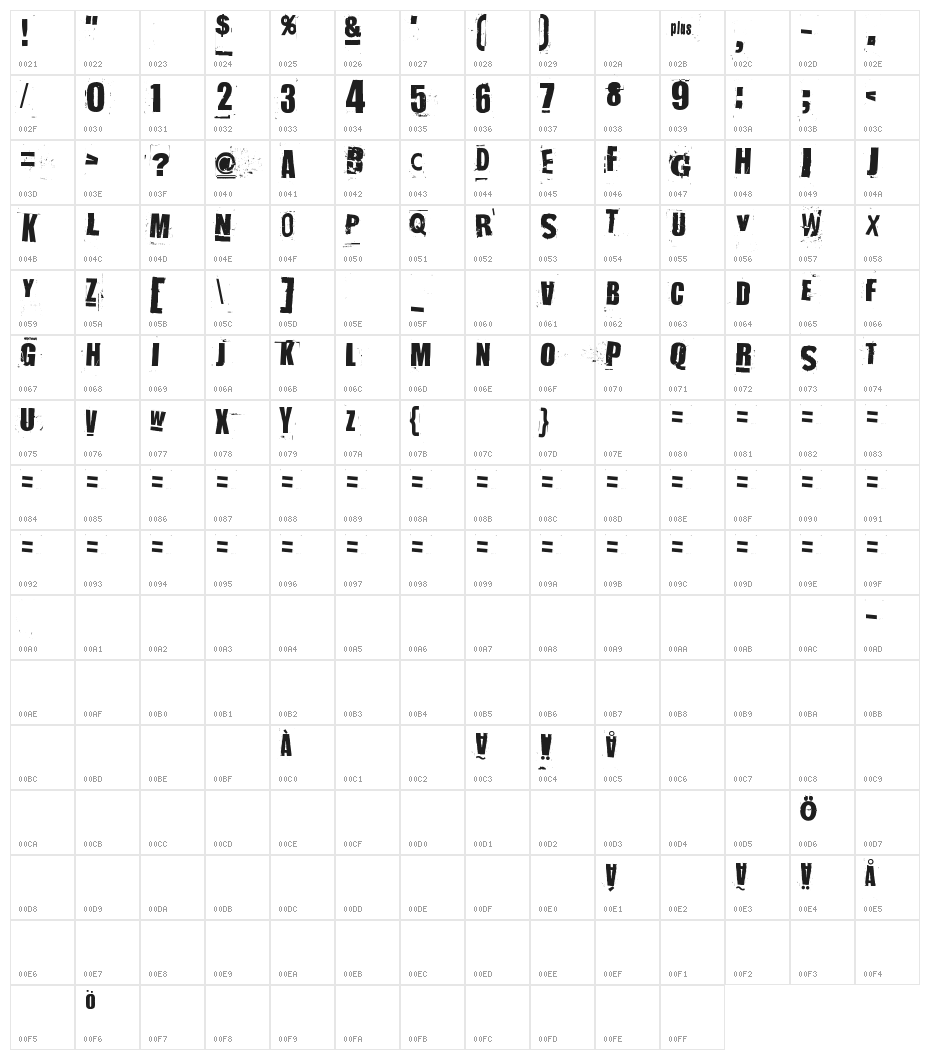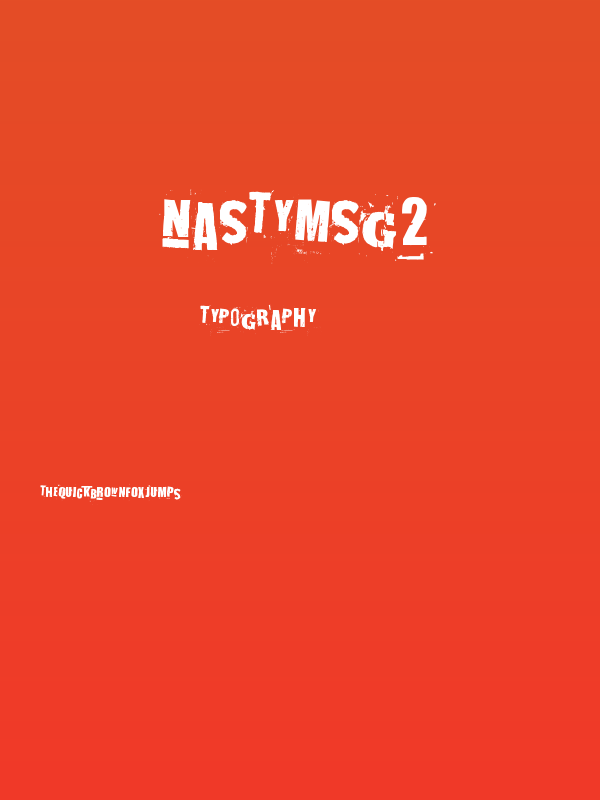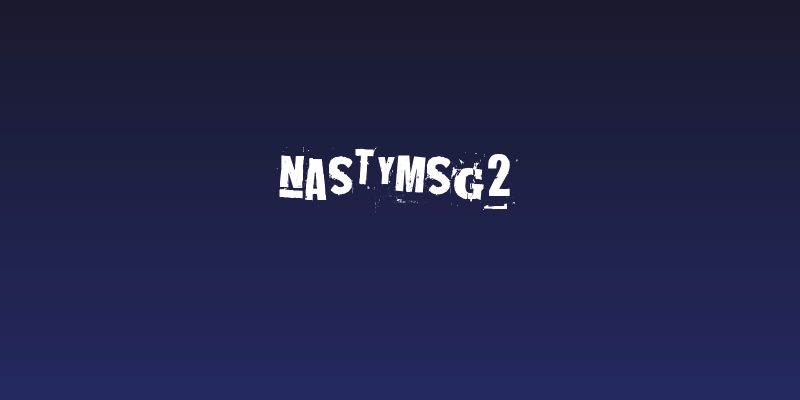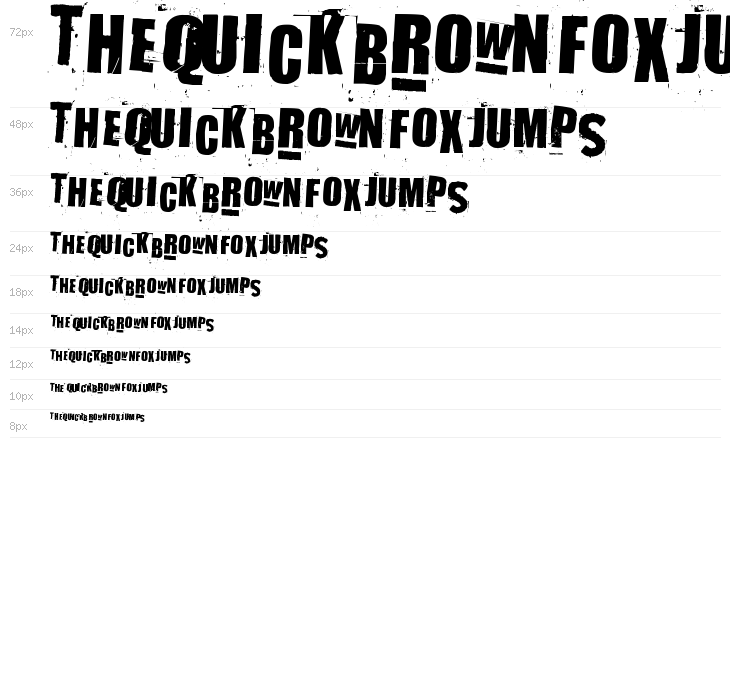
NastyMSG2 Font
✎ Distorted Eroded
| Categorie | Distorted Eroded |
| Stile generale | Grunge, Edgy |
| Caso d'uso | Headlines, Posters, Branding |
| Progetti proposti | Ideal for music posters, album covers, edgy branding, or any project needing a rebellious touch. |